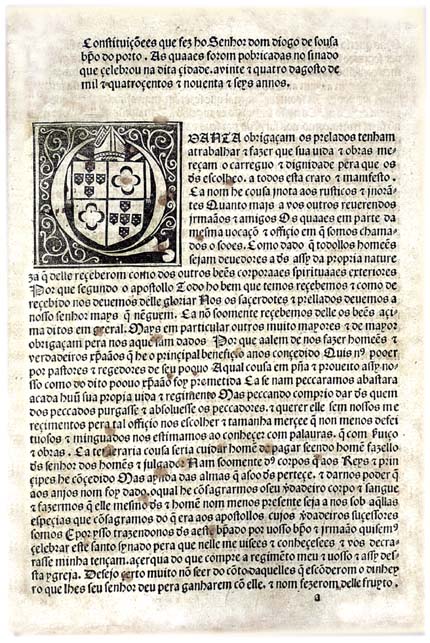
Rodrigo Álvares (séc. XV)O primeiro prototipógrafo português. Este mestre de emprentar livros é o impressor das «Constituições» do Bispo do Porto, saídas do prelo em 1497. Do prelo de Rodrigo Álvares são conhecidas duas obras: As Constituições que fez ho Senhor dom Diogo de Sousa e Os Evangelhos e Epístolas com as suas exposições en romãce. Ambas obras foram impressas em 1497.A 4 de Janeiro de 1497 foi publicada na cidade do Porto a obra Constituições que fez o Senhor Dom Diogo de Sousa, Bispo do Porto, livro impresso pelo primeiro prototipógrafo português, o transmontano Rodrigo Álvares. (Para plena satisfação dos historiadores nacionalistas, que acreditam que Álvares foi mais português que o judeu Gacon... (Há patrioteiros que preferem ignorar que Portugal nesta época ainda era um país multicultural, onde coexistiam pelo menos três culturas e quatro idiomas: cristã, islâmica e judaica, e latim, português, árabe e hebraico). Na obra de Rodrigo Álvares está visível a influência dos prototipógrafos alemães, pois este livro foi impresso com letra gótica, e esses tipos móveis ou vinham da Alemanha ou dos impressores alemães estabelecidos em Espanha. Rodrigo Álvares nasceu em Vila Real; esteve activo como impressor e editor no Porto. Aqui, como colaborador do bispo Diogo de Sousa, imprimiu as Constituições Sinoidais e os Evangelhos e Epístolas, ambas obras em 1497.
Dos Evangelhos e Epístolas existe hoje apenas um único exemplar completo. Esta obra foi publicada e impressa pela primeira vez em Sevilha em 1485, na oficina do alemão Pablo Hurus e, em 1493, na cidade de Salamanca por um impressor desconhecido. A tradução em português será do próprio Rodrigo Álvares, a partir desta última edição. A impressão foi feita com tipos de letra gótica, em dois tamanhos, em 25 de Outubro de 1497. A composição é a duas colunas e tem 62 gravuras, 14 das quais foram repetidas. A foliação é de 200 fólios e a imposição é em cadernos de 4 folhas em papel grosso. As relações entre o bispo Diogo de Sousa e Rodrigo Álvares continuaram depois de 1497; é possível que o tipógrafo nortenho tenha impresso, por volta de 1506, no Porto ou em Braga, umas segundas Constituições de Dom Diogo obra da qual existe um exemplar na Biblioteca Pública Municipal do Porto, sem indicação de data ou local de impressão. Para além destas impressões, especulou-se que Álvares teria sido impressor de breviários. O romancista Aquilino Ribeiro escreveu que Rodrigo Álvares aprendera o ofício com o tipógrafo alemão Pablo Hurus em Saragóça, hipótese que o bem esclarecido especialista Artur Anselmo refuta. Outros são da opinião que terá aprendido em Salamanca, ou Braga, na oficina do alemão João Gherlin. Rodrigo Álvares poderia ter sido discípulo de Gherlin e dele teria recebido os tipos para os trabalhos realizados no Porto, os quais são um ampliação das matrizes do Breviarium Bracharense de 1494. LinksConsulte a grande colecção de incunábulos da biblioteca japonesa National Diet Library, em www.ndl.go.jp/incunabula |